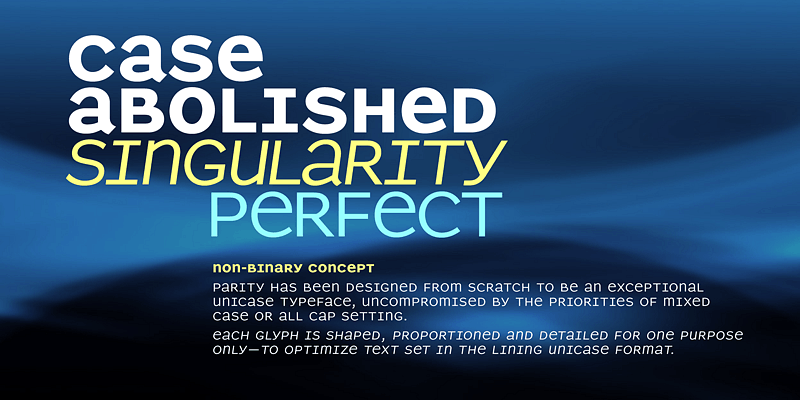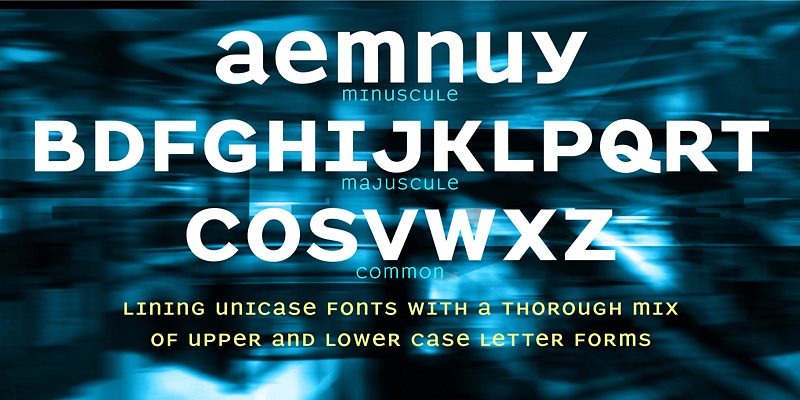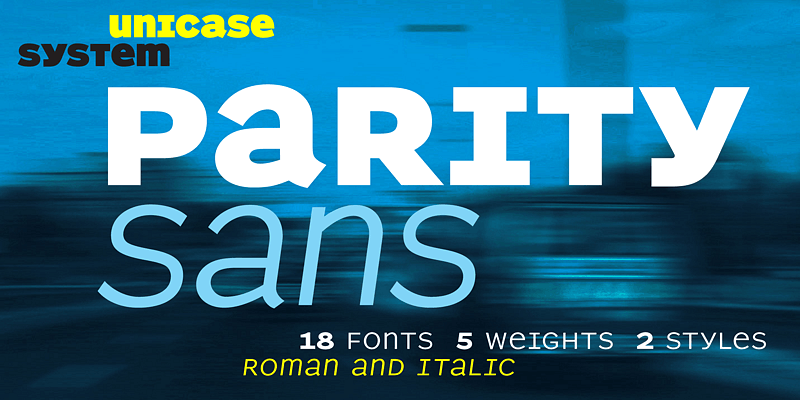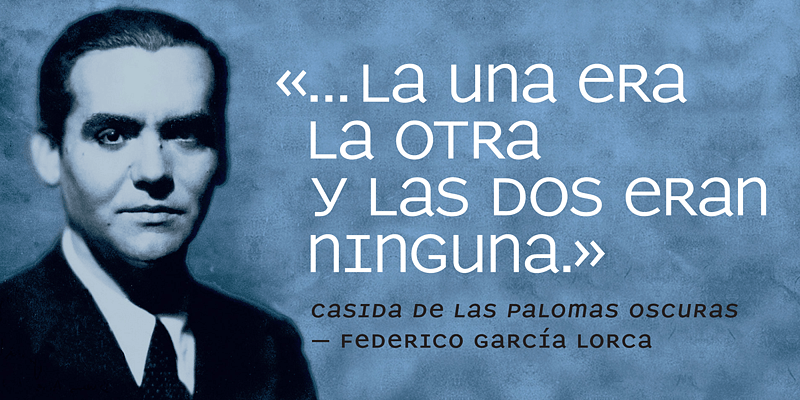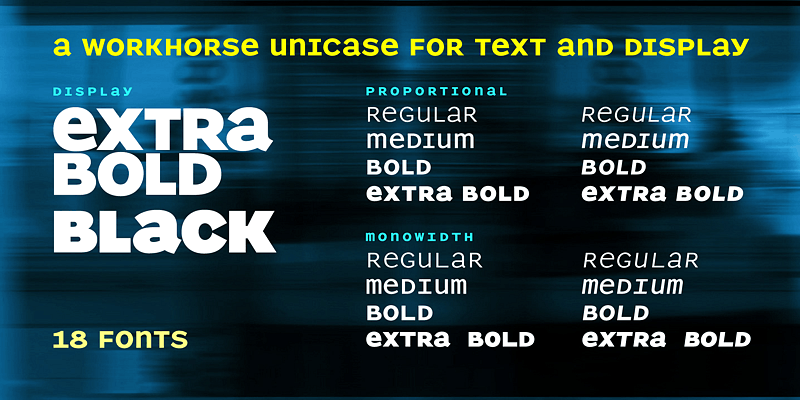
Conçue à l’origine comme une expérience unique (une seule taille et unicamérale), Parity Sans a été développée pour intégrer des polices proportionnelles. Exceptionnelle pour une conception unicamérale, la grande famille permet des hiérarchies complexes de caractéristiques, avec des italiques, six graisses et des styles de texte et d’affichage.
Telles sont les conceptions de Nick Shinn : profondément enracinées dans l’évolution continue de la meilleure tradition typographique européenne et nord-américaine, solidement ancrées dans le texte, offrant toutes les caractéristiques d’une typographie experte, élégantes, et portant une attention incomparable aux détails.
Fort de son expérience de directeur artistique et de graphiste acquise dans les 80 et 90, ayant compté parmi les premiers à travailler sur les médias numériques, Nick Shinn a lancé Shinntype, l’une des premières fonderies de caractères en ligne, en 1998. Shinntype dispose aujourd’hui d’un important catalogue très éclectique de polices uniques, adaptées aux tendances contemporaines.